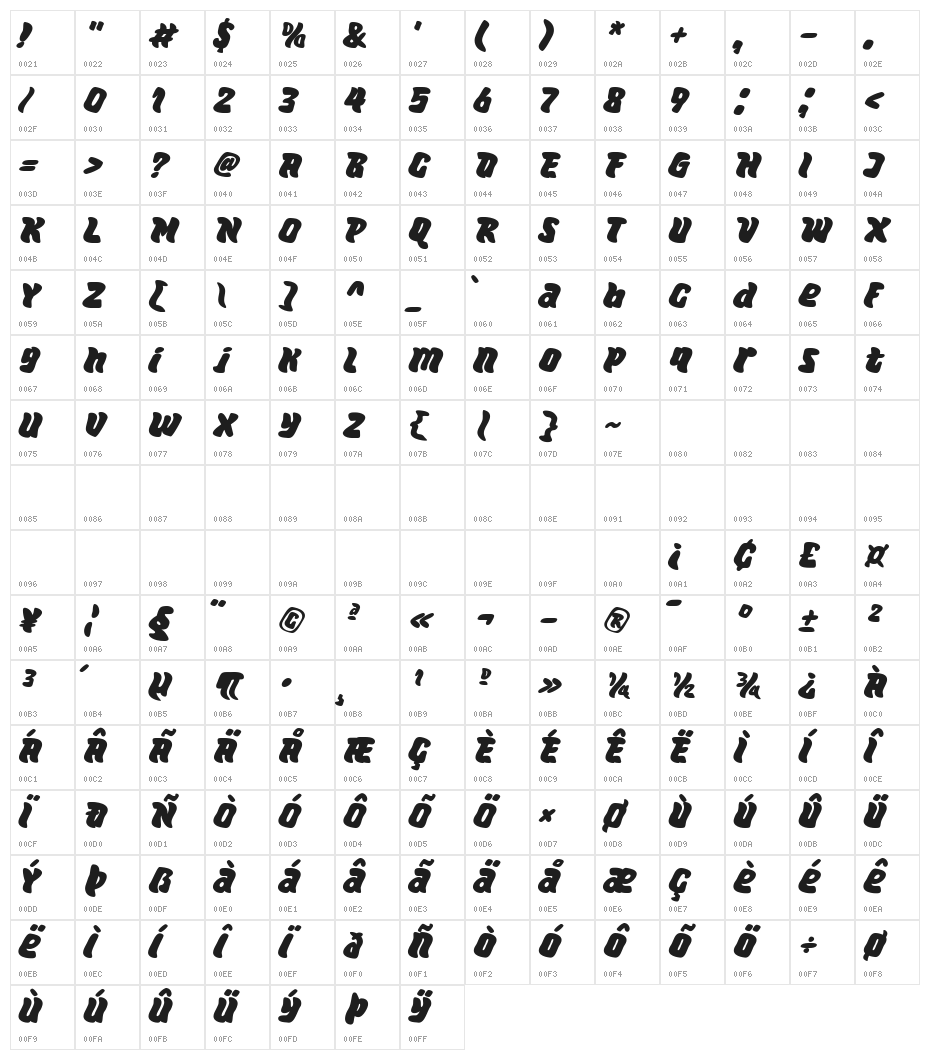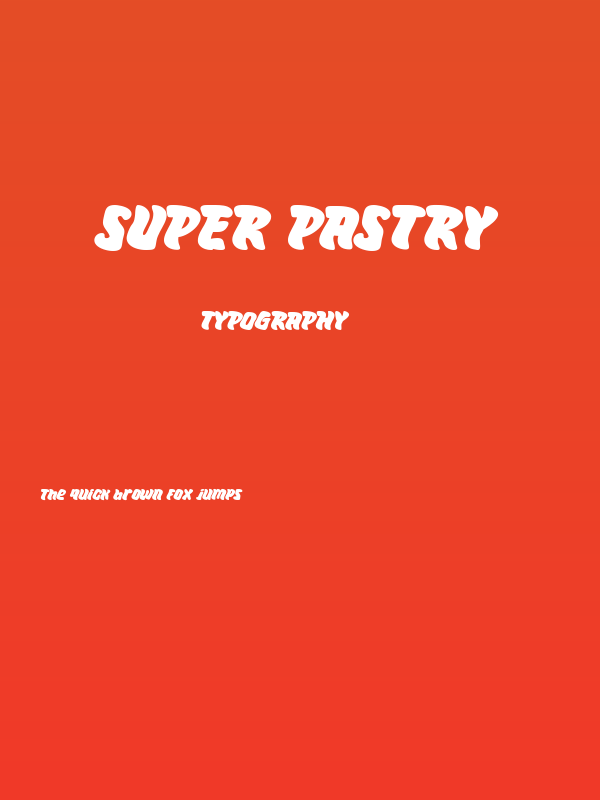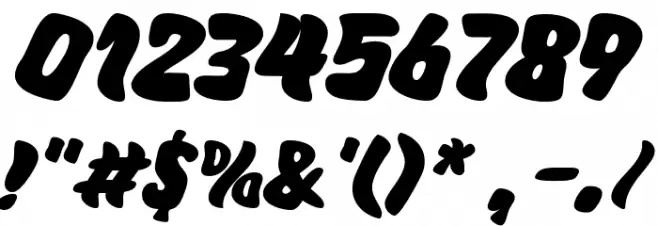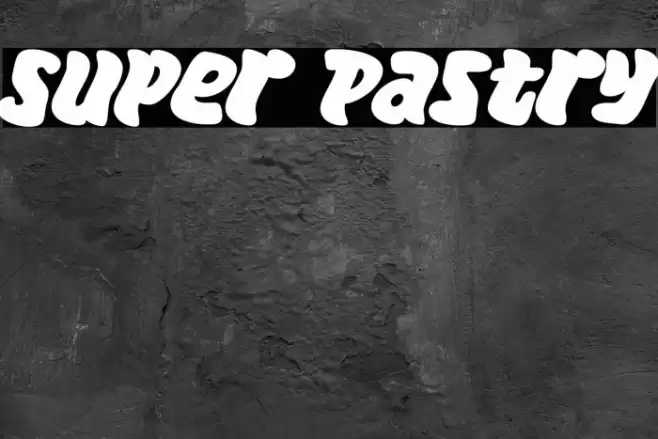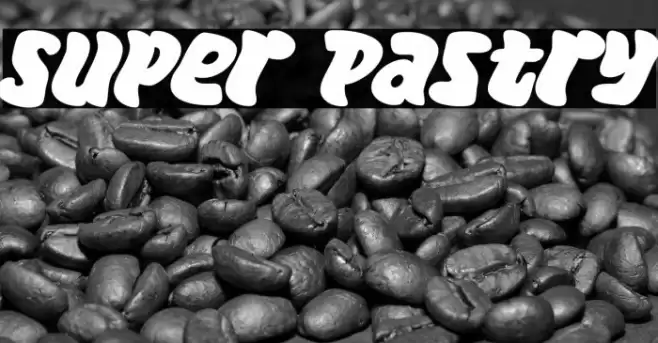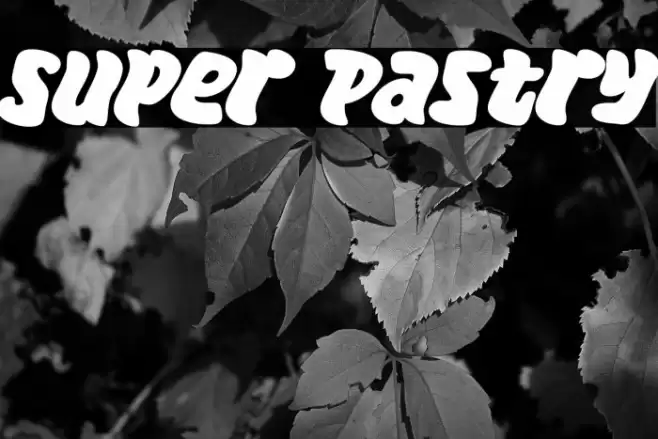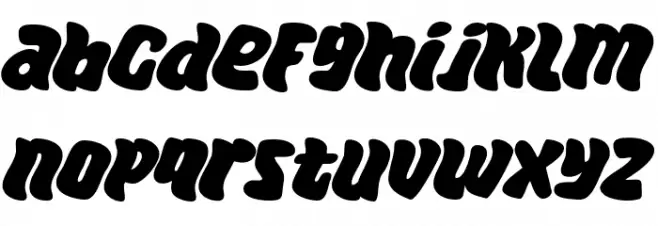
Super Pastry Font
| Gesamtstil | Playful, Energetic |
| Anwendungsfall | Logos, Headlines, Posters |
| Vorgeschlagene Projekte | Ideal for children's books, playful branding, posters, and event invitations. |